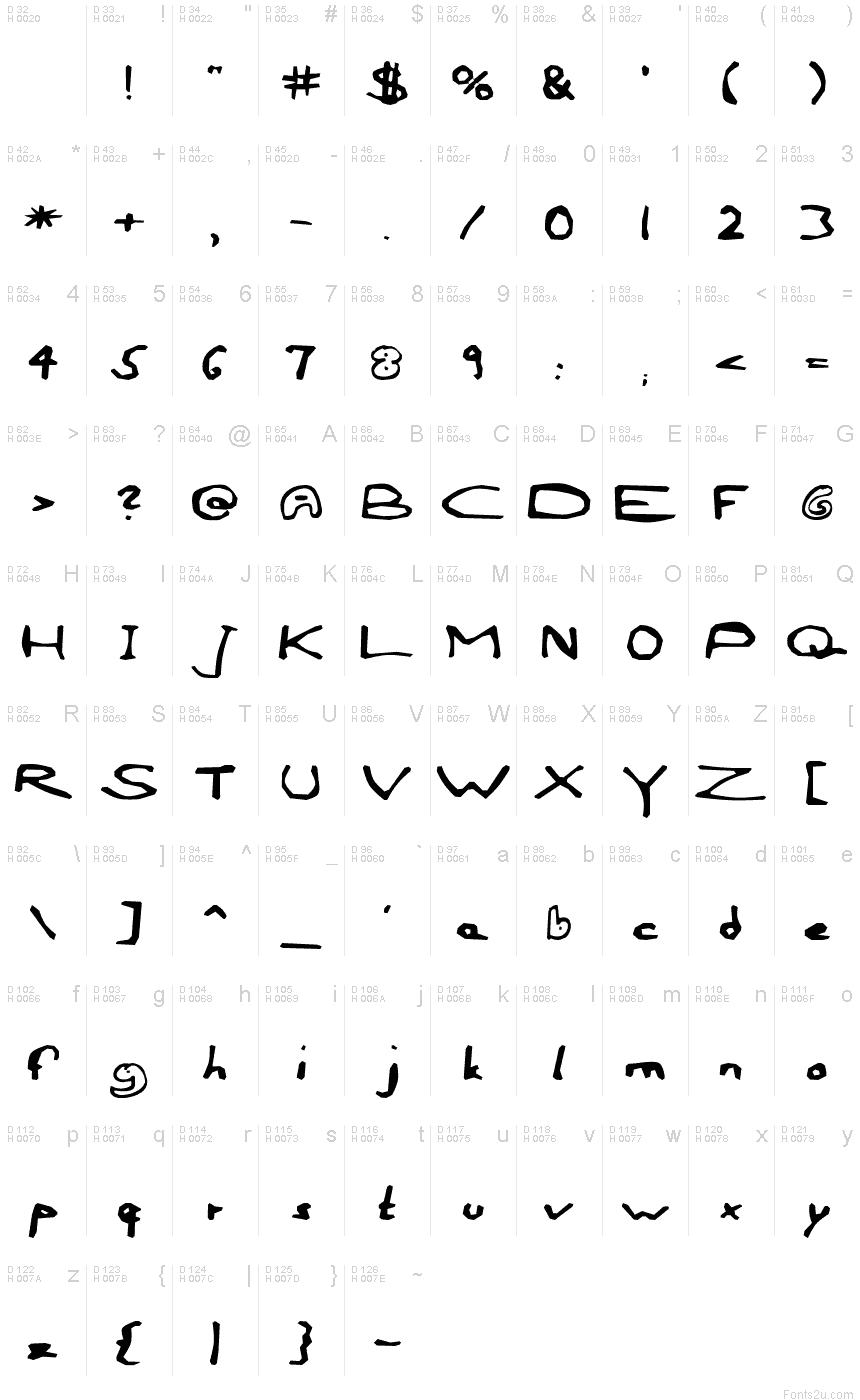
AEZ Outline Frenzy-1 to darmowy krój pisma ekspozycyjnego w stylu graffiti, zbudowany z poszarpanych, improwizowanych kształtów liter. Szerokie poziome pociągnięcia łączą się z ostrymi rogami, nierównymi konturami i nagłymi przejściami między otwartymi a pełnymi kształtami, co nadaje literom wygląd wyklejanki.
Jego charakter streetartowy pasuje do plakatów muzycznych i grafiki eventowej skierowanej do publiczności punkowej, deskorolkowej lub undergroundowej. Gadżety i oprawy albumów mogą wykorzystywać nieregularną konstrukcję, aby sugerować odręczne tagi, kserowane ulotki i surowe prace markerem. Na tle tekstur aerozolowych, kolaży z rozdartego papieru lub kanciastych ilustracji litery stają się częścią dzieła sztuki, a nie konwencjonalną warstwą typograficzną.